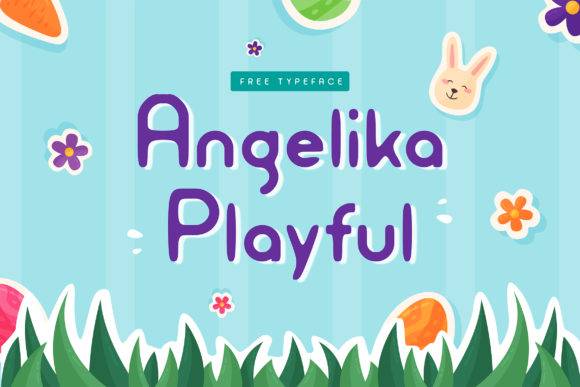
Fuente divertida Angelika para imprimibles divertidos y decoración de fiestas
Angelika Playful es una fuente brillante y enérgica, diseñada para realzar diseños imprimibles, decoración para fiestas y manualidades alegres. Sus formas redondeadas y su agradable espaciado entre caracteres la hacen ideal para fiestas infantiles, eventos familiares y regalos hechos a mano que necesitan un toque divertido.
Esta fuente aporta ligereza y accesibilidad a tu trabajo creativo. Ya sea que diseñes invitaciones para fiestas, pancartas imprimibles o hojas de pegatinas, Angelika Playful ofrece claridad con un toque de encanto que destaca tanto en formato impreso como digital.
Para quién es
- Organizadores de fiestas y diseñadores de eventos
- Maestros y creadores de educación en casa
- Artesanos de bricolaje y creadores de imprimibles
- Diseñadores de pegatinas y planificadores digitales
- Padres creando materiales para fiestas en casa
Lo que puedes hacer
- Banners e invitaciones de cumpleaños
- Juegos de fiesta y decoración imprimibles
- Pegatinas y títulos para scrapbooking
- Etiquetas de regalo, etiquetas y carteles de regalo
- Materiales educativos e imprimibles
Por qué te encantará
- Diseño caprichoso y amigable.
- Perfecto para proyectos imprimibles festivos.
- Legibilidad clara en todos los tamaños
- Ideal para eventos infantiles y diseños alegres.
P: ¿Qué estilo es Angelika Playful?
A: Angelika Playful es una fuente caprichosa, redonda y enérgica, perfecta para decoración de fiestas y diseños imprimibles.
P: ¿Puedo usar esta fuente para invitaciones de cumpleaños infantiles?
R: Por supuesto. Es una excelente opción para crear invitaciones y carteles para fiestas divertidos y coloridos.
P: ¿Puedo crear juegos y carteles imprimibles con esta fuente?
R: Sí, es perfecto para diseñar juegos imprimibles, pancartas, carteles y otras manualidades con temática de fiesta.